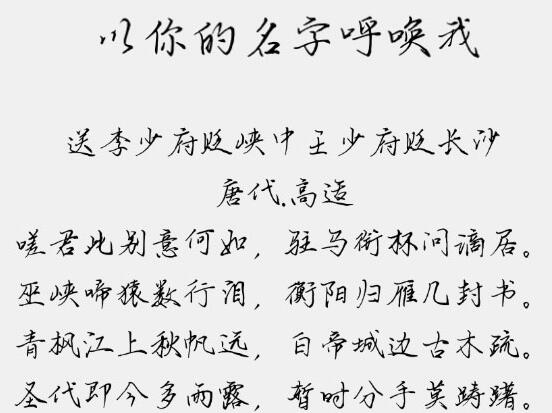
以你的名字呼唤我是一款十分好用,且非常漂亮的中文字体,同时也是由文道字库倾情发布的作品,字体笔触粗细适中,字型略带潦草,却又无比的清晰,给人一种悬崖峭壁的视觉感,适应于报纸和杂志和书籍中常用字体海报、个性促进品牌标志设计、文本装潢、信息展示、篆刻制模英文、数据制作、装潢设计、视觉设计、字帖等一切合法应用场景,有喜欢的朋友可免费下载收藏。